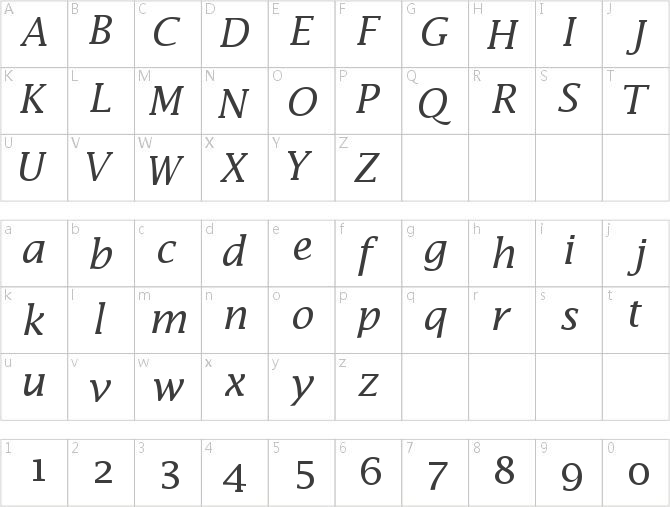
MachadoMathAlternateExtSSK 詳情頁
MachadoMathAlternateExtSSK字體字庫是一款讓人賞心悅目、百看不厭的英文字體,適合各類廣告和產(chǎn)品包裝設(shè)計應(yīng)用,字體大小0.04MB,格式為ttf字體,上傳用戶是曾紹文,作者/版權(quán)方為未知